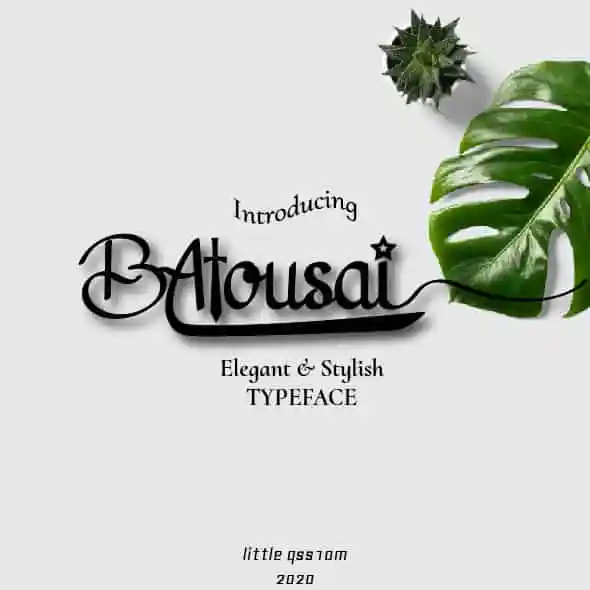
Batousai Calligraphy Font – Fonte Grátis
Batousai Calligraphy Font
Batousai é uma fantasia elegante, com um charme clássico que se traduz não apenas em leitura fácil, mas também em uma escrita aparentemente descomplicada e divertida de usar. Ideal para adicionar um toque único aos projetos mais diversos como logotipos de signatura, capas de álbuns, cartões de visita, marcações nas fotos ou até mesmo as citações dos seus clientes. Se você é designer gráfico buscando um elemento de design que seja tanto funcional quanto original, Batousai é uma fonte para destacar. Suas formas suaves e atraentes permitem criar designs impressionantes em um amplo espectro de projetos. O uso desta font não só dará um toque especial aos seus trabalhos, mas também certamente será um ponto de encontro entre você e seu público-alvo. Batousai é perfeito para aqueles que desejam manter a simplicidade nos seus design projectos ao mesmo tempo em que adicionam uma leve dose de originalidade. É uma escolha óbvia quando se trata de adicionar um toque personalizado às suas criações, seja você criando logotipos sofisticados ou simplesmente querendo dar um novo encanto às suas fotos. Com Batousai, seu design terá o charme e a elegância necessários para que ele destaque-se em qualquer projeto. Sem dúvida alguma, esta fonte é uma excelente opção tanto para designers iniciantes quanto aqueles com anos de experiência.